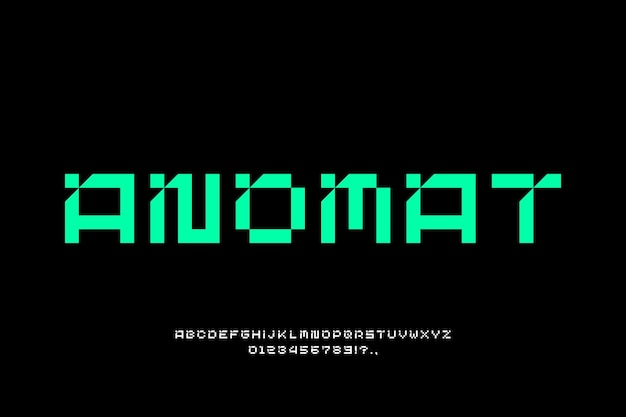
Cyberpunk font retro digital typesæt Grønt hacker alfabet pixel usædvanlig type Cyber tech bogstaver til mikrochip hud netværk ai database UI Vektor typografisk design